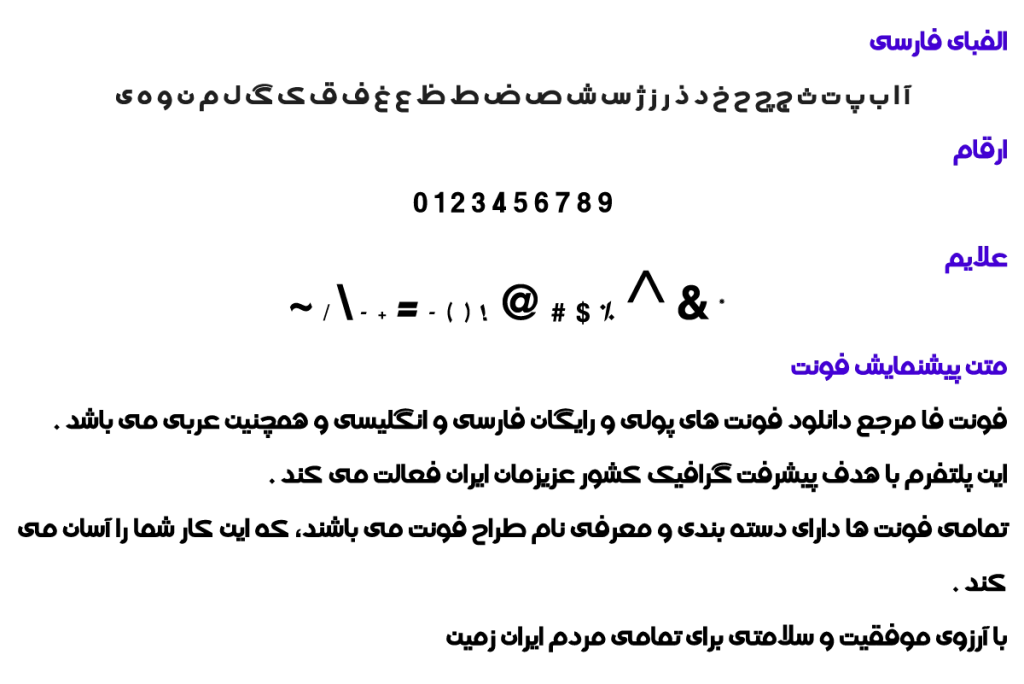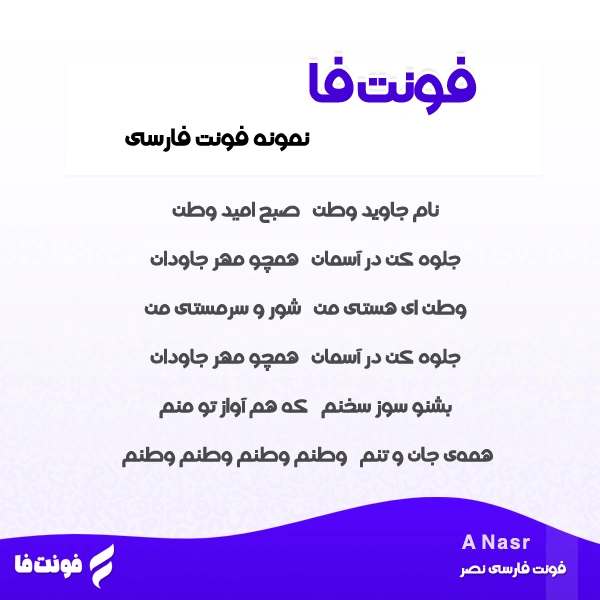
فونت فارسی نصر – A Nasr
نوع فونت: فونت عنوان
توضیحات و معرفی فونت نصر
فونت فارسی نصر ( A Nasr ) از مجموعه فونت های آزاد می باشد، و نیز نوع فونت عنوان می باشد.
فونت خوشگل مربوط در سال 1390 طراحی و ساخته شده است.
و نیز فونت A Nasr در یک وزن پر رنگ است.
- A Nasr Bold
شعر فارسی با حال و هوای وطن، نوشته شده با این تایپ فیس، در عکس زیر قابل مشاهده است.